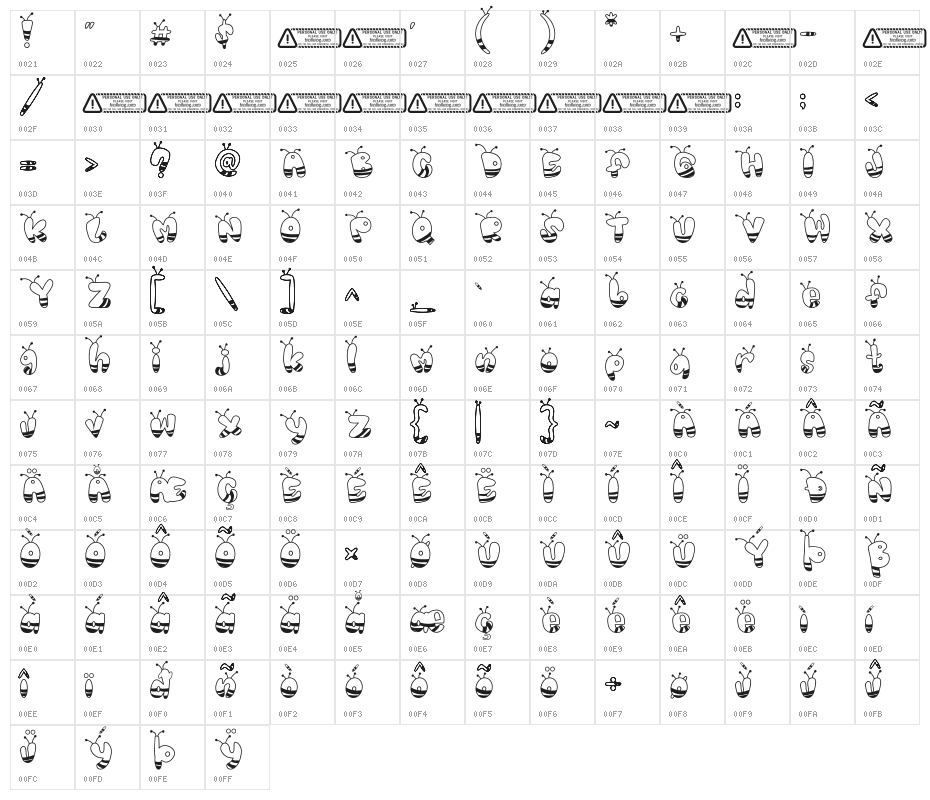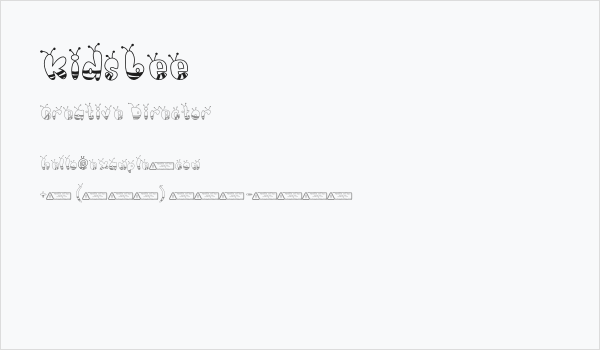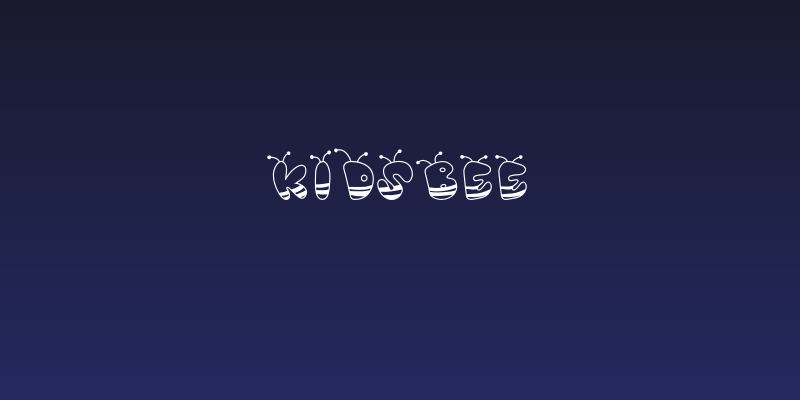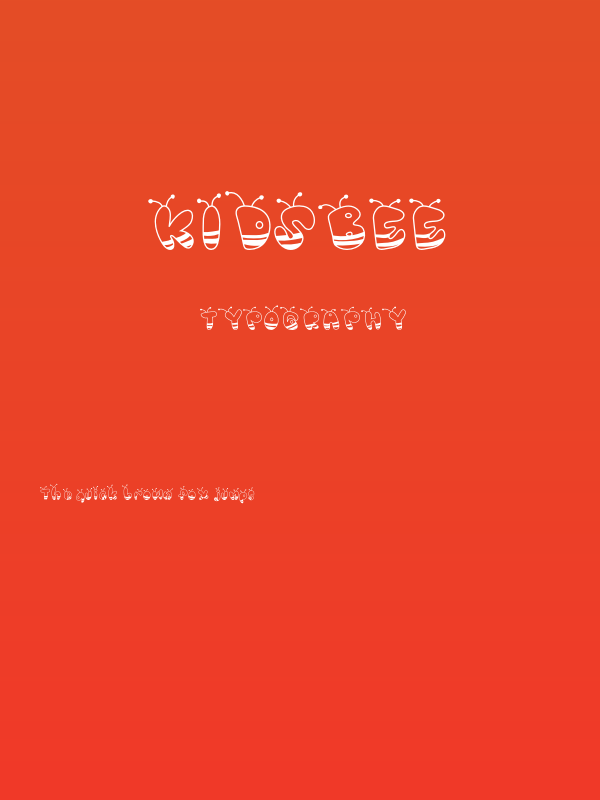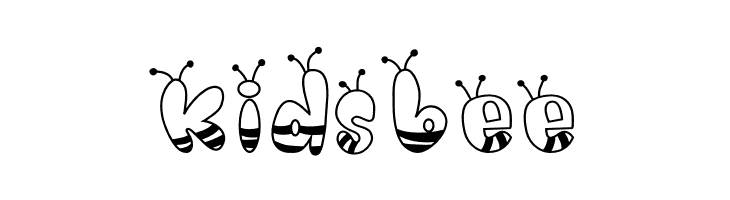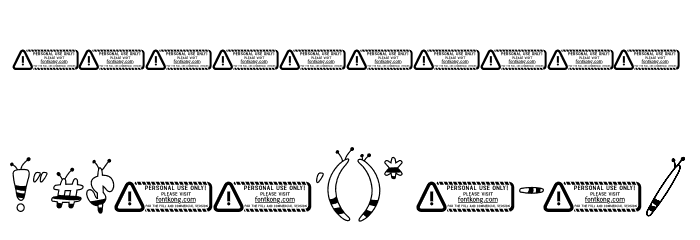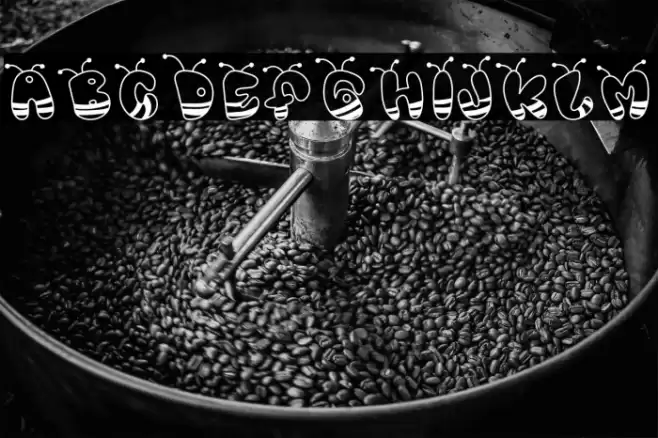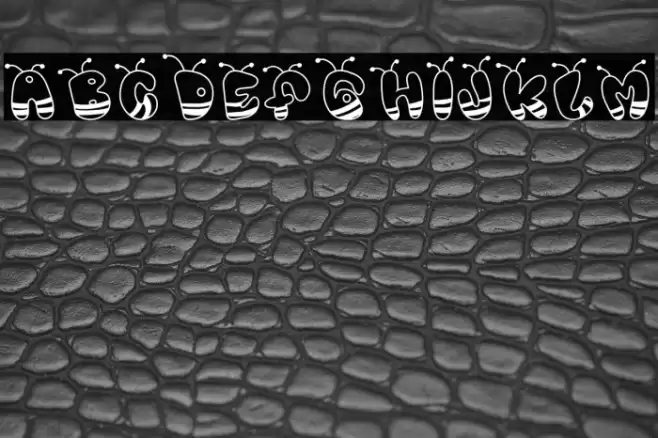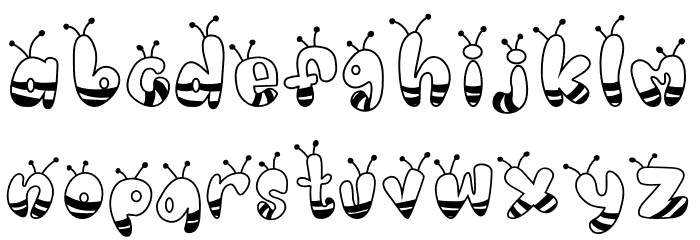
Kidsbee Font
| Style général | Playful, Whimsical |
| Cas d'utilisation | Headlines, Logos, Children's materials |
| Projets proposés | Ideal for children's books, educational materials, playful branding, and creative invitations. |